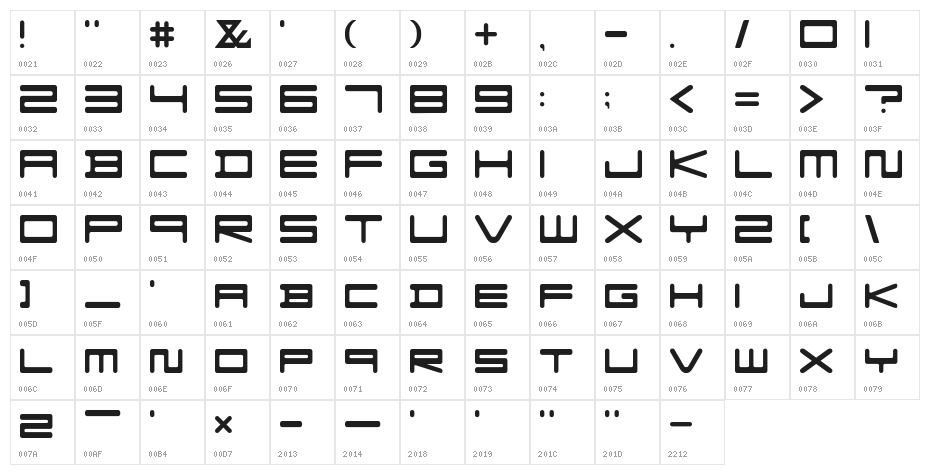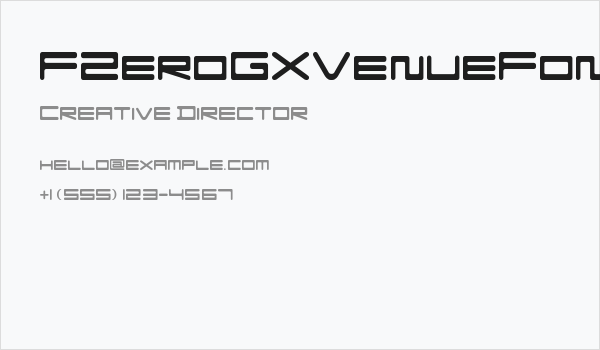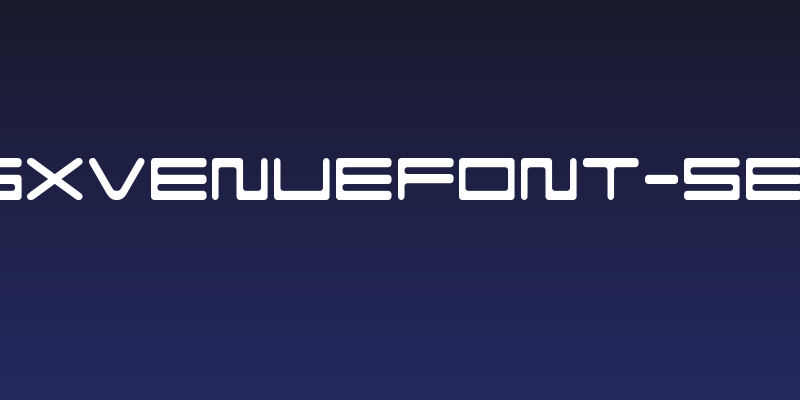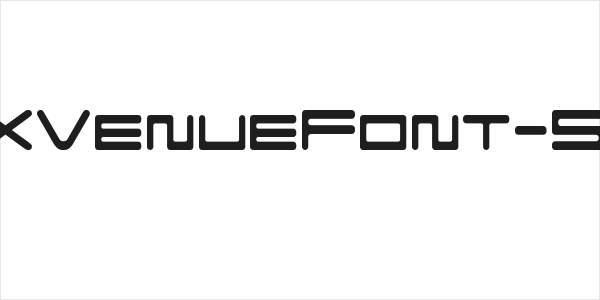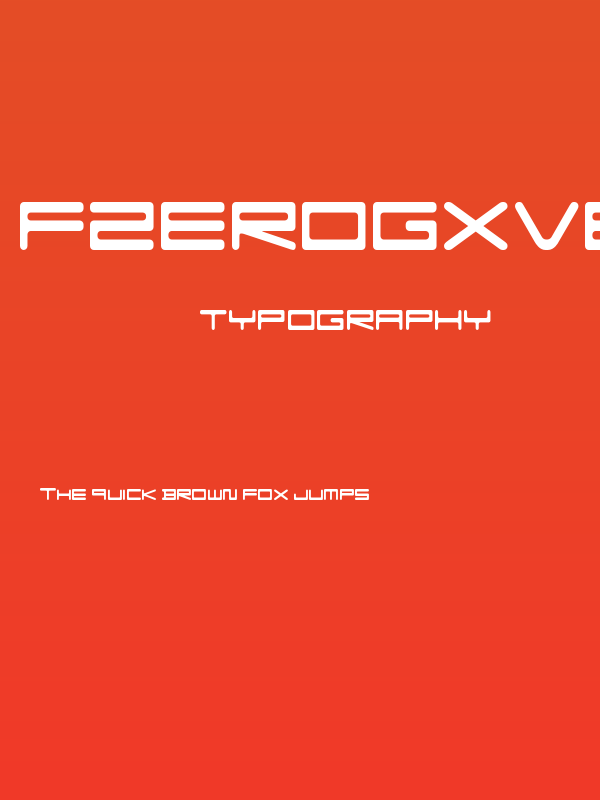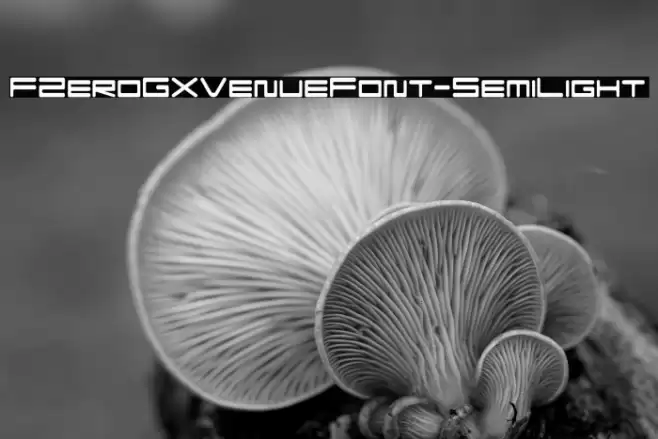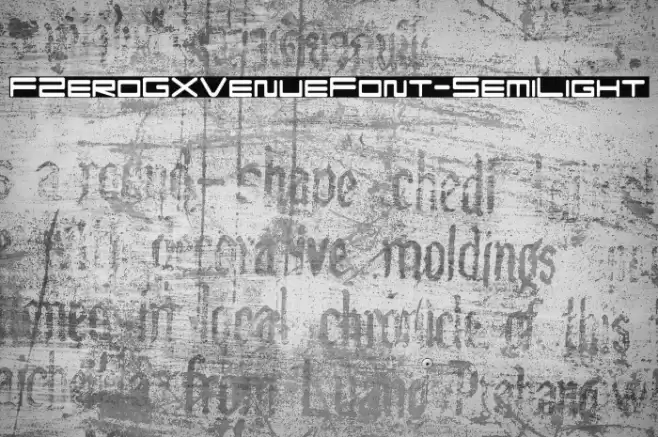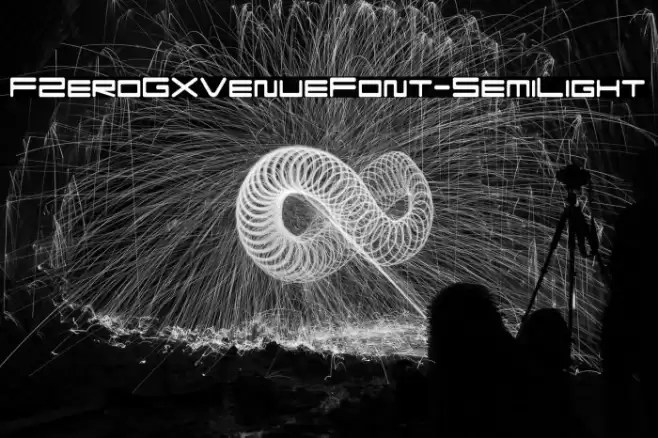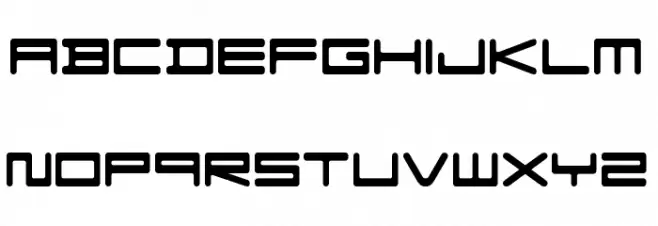
FZeroGXVenueFont-SemiLight Font
| समग्र शैली | Futuristic |
| उपयोग का मामला | Logos, Headlines, Digital Interfaces |
| सुझाए गए प्रोजेक्ट | Ideal for technology branding, digital interfaces, video game design, and sci-fi themed projects. |